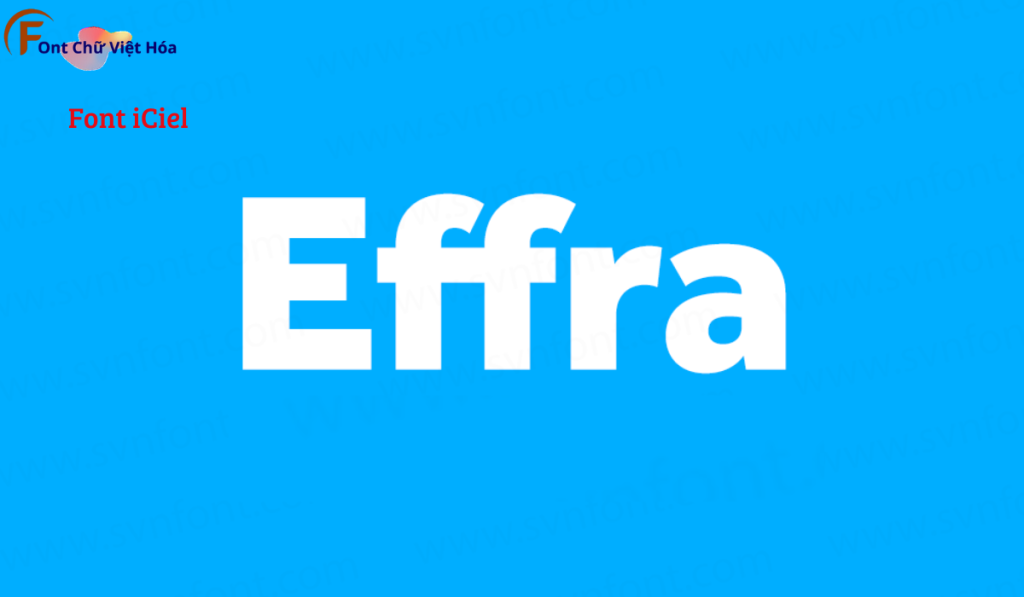
Font iCiel Effra Việt Hóa
Tác giả: iCiel Effra
Bộ Font: iCiel
Phân loại: Độc đáo
Kiểu chữ: Sans-serif
Độ dày: Regular, Medium, Bold
Font iCiel Effra Việt Hóa, thuộc bộ font iCiel, là font sans-serif hiện đại, nổi bật với các nét chữ rõ ràng và độ dày đa dạng. Font này có các đường nét gọn gàng, dễ đọc, tạo cảm giác sáng tạo và chuyên nghiệp. Font iCiel Effra Việt Hóa lý tưởng cho các dự án thiết kế như thiệp mời, bìa sách, và tài liệu văn phòng. Việc Việt hóa font giúp người dùng dễ dàng tích hợp vào các thiết kế tiếng Việt, mang lại sự tiện lợi và nâng cao tính thẩm mỹ.